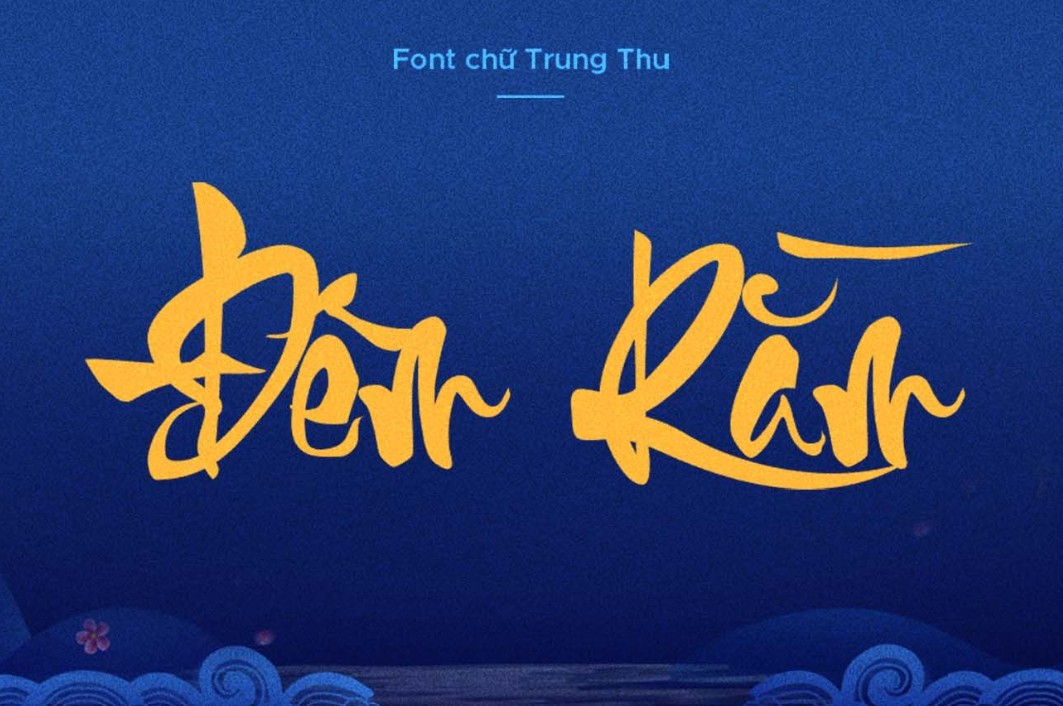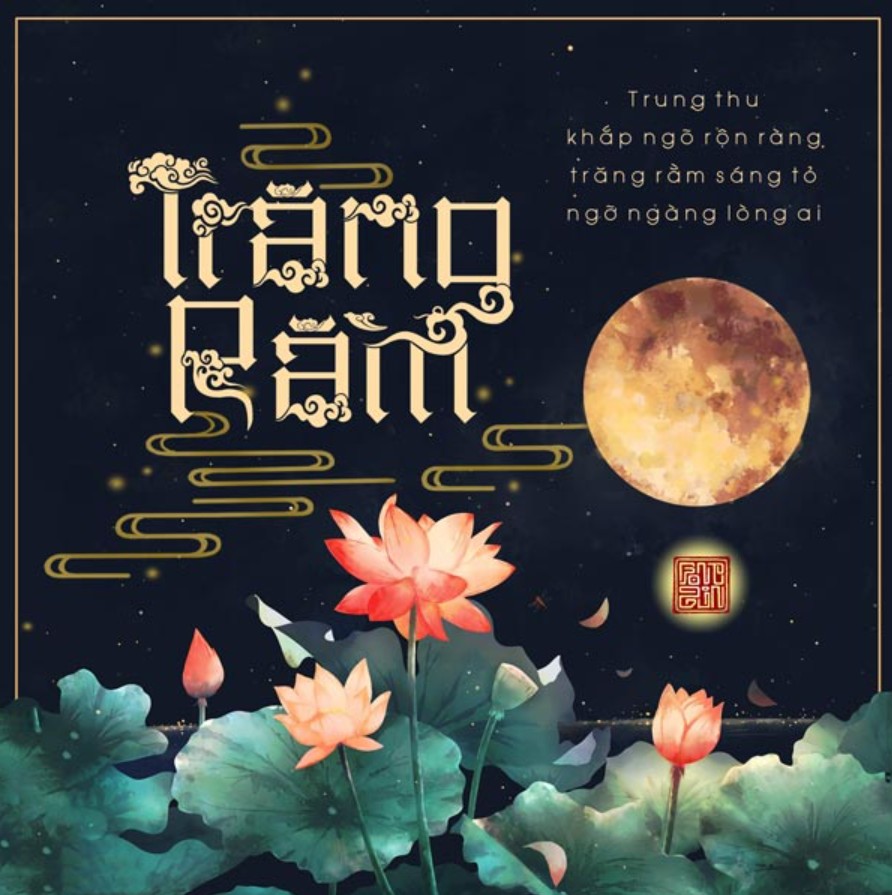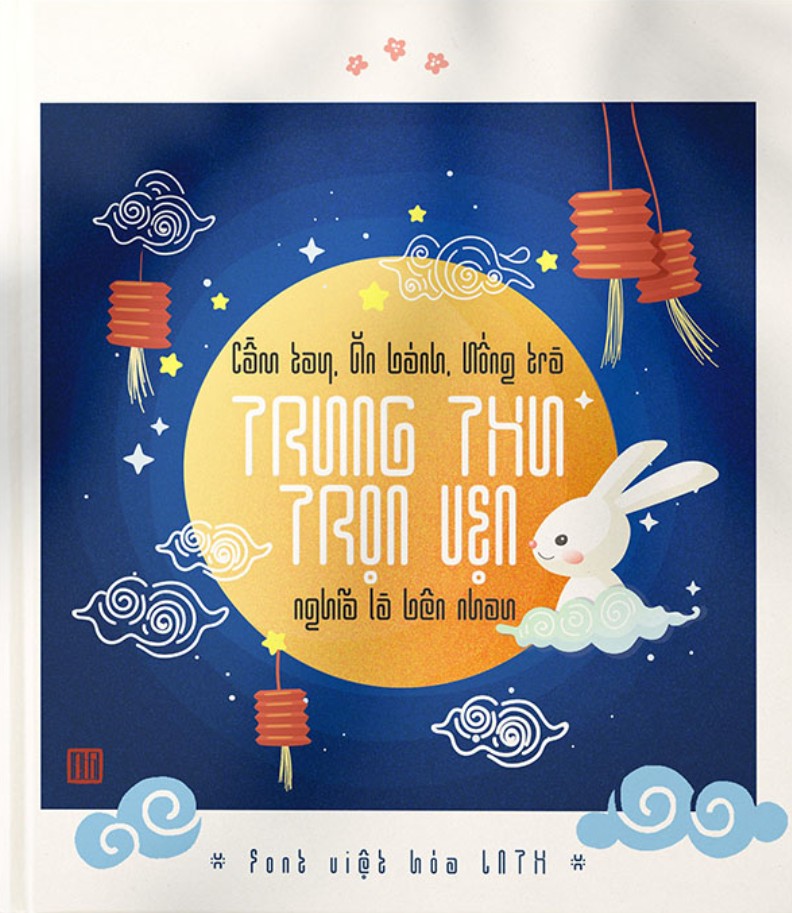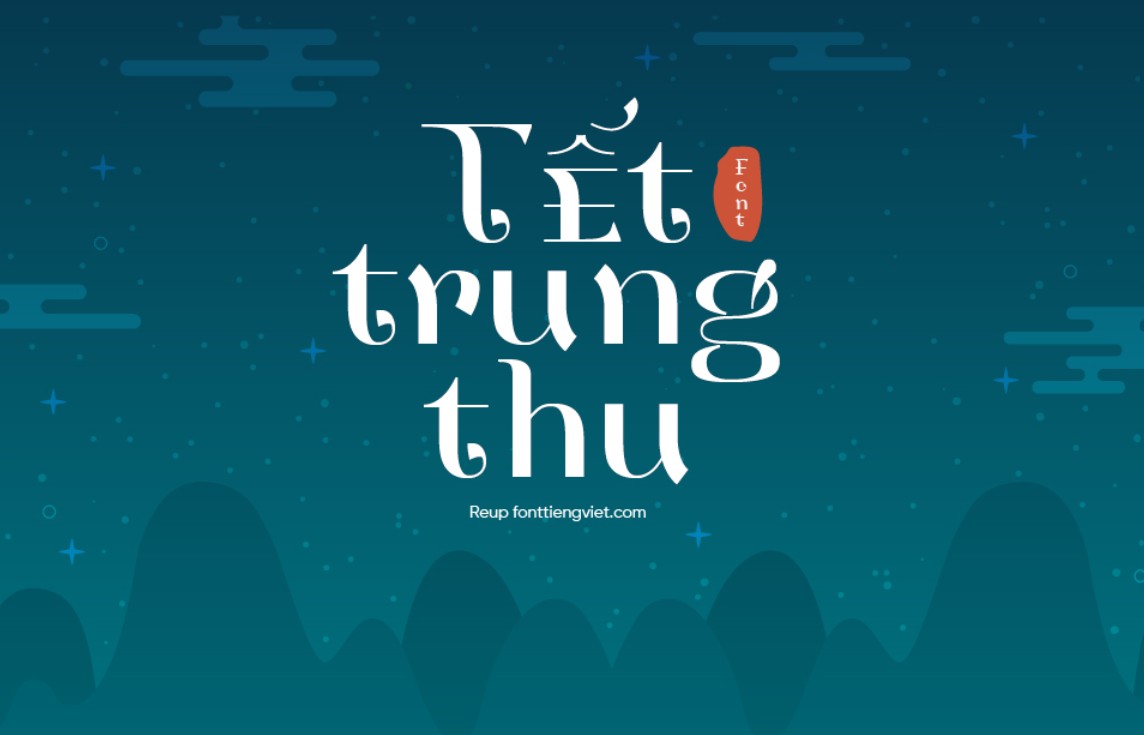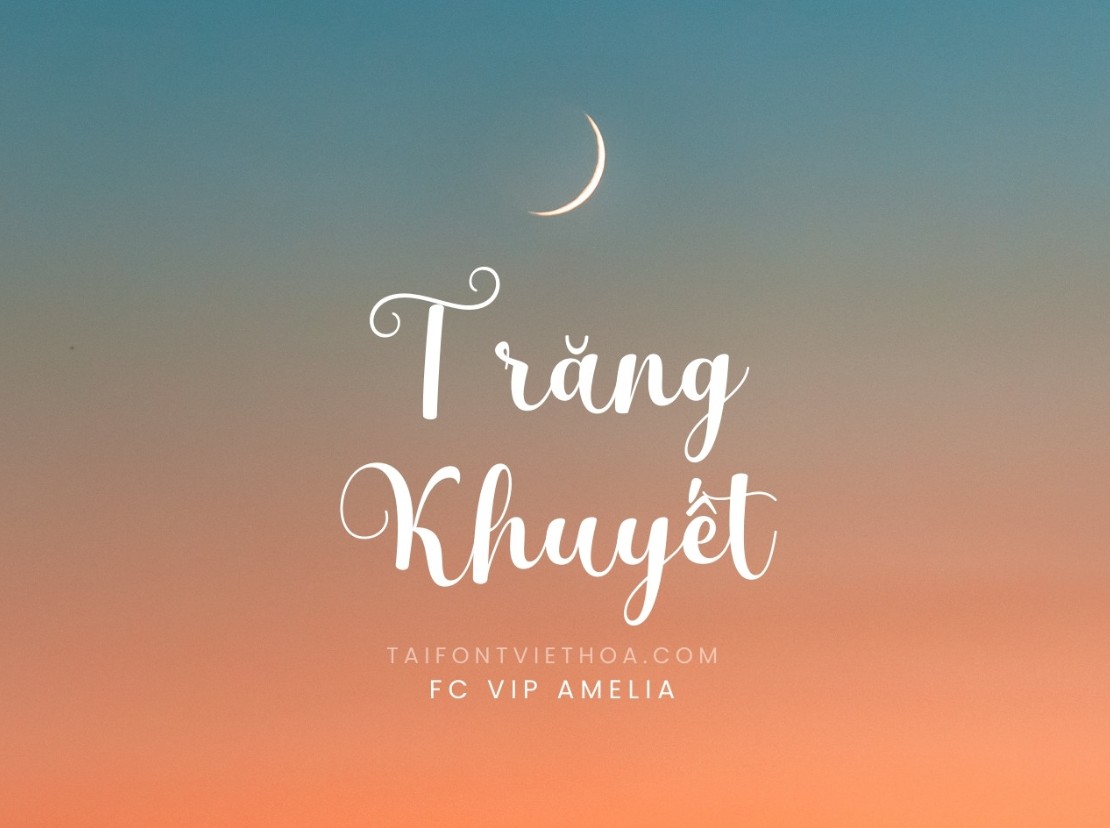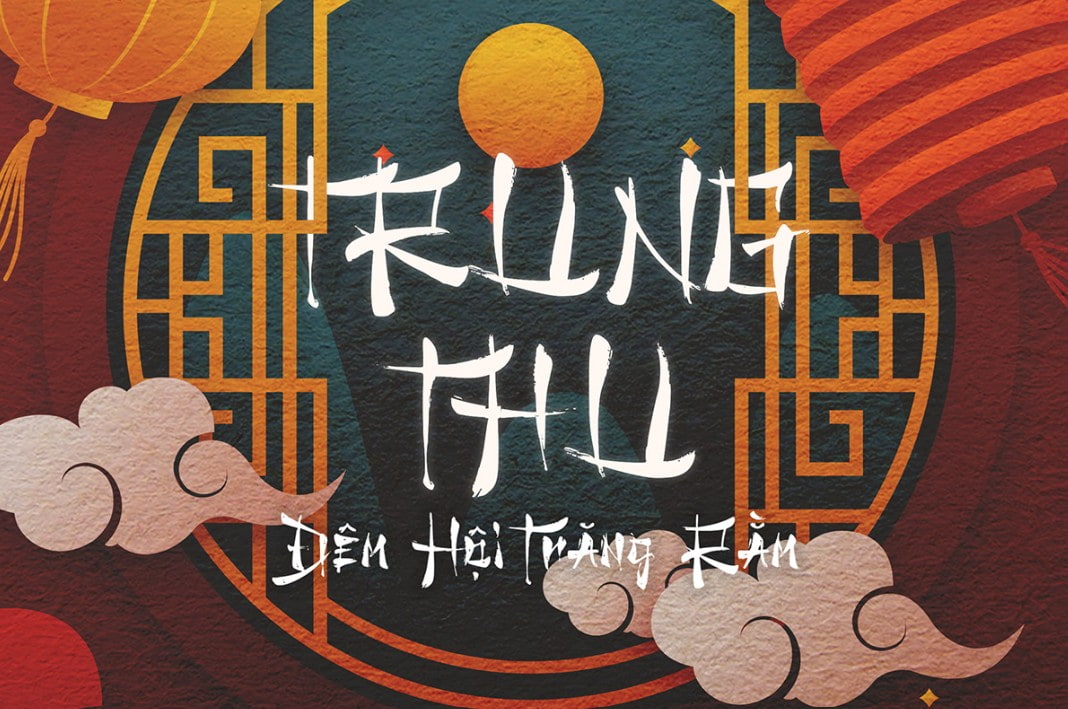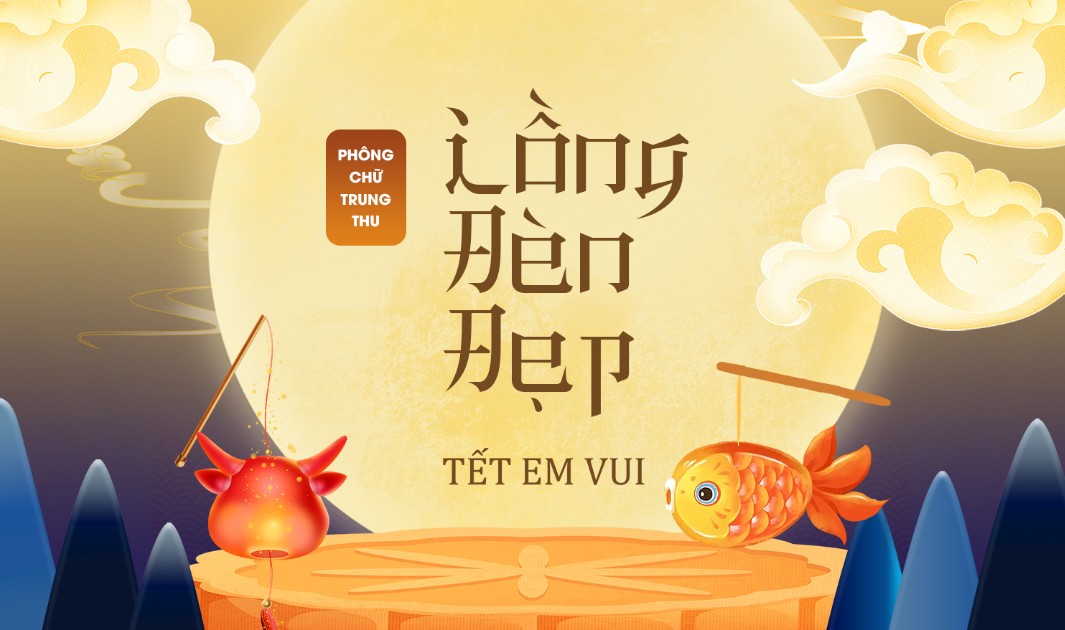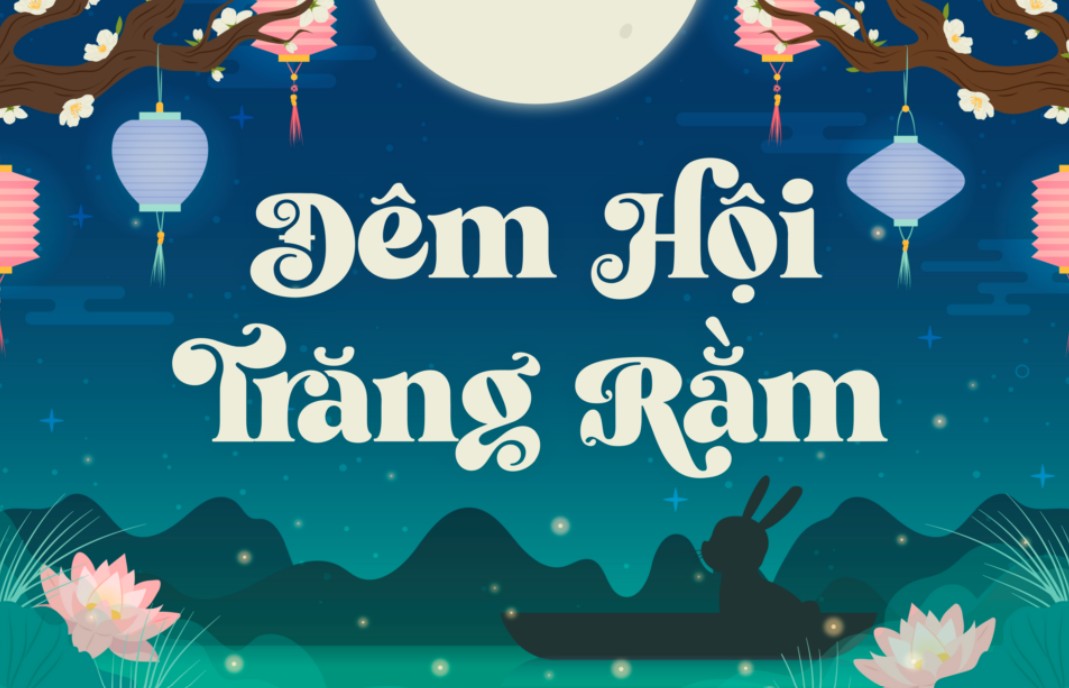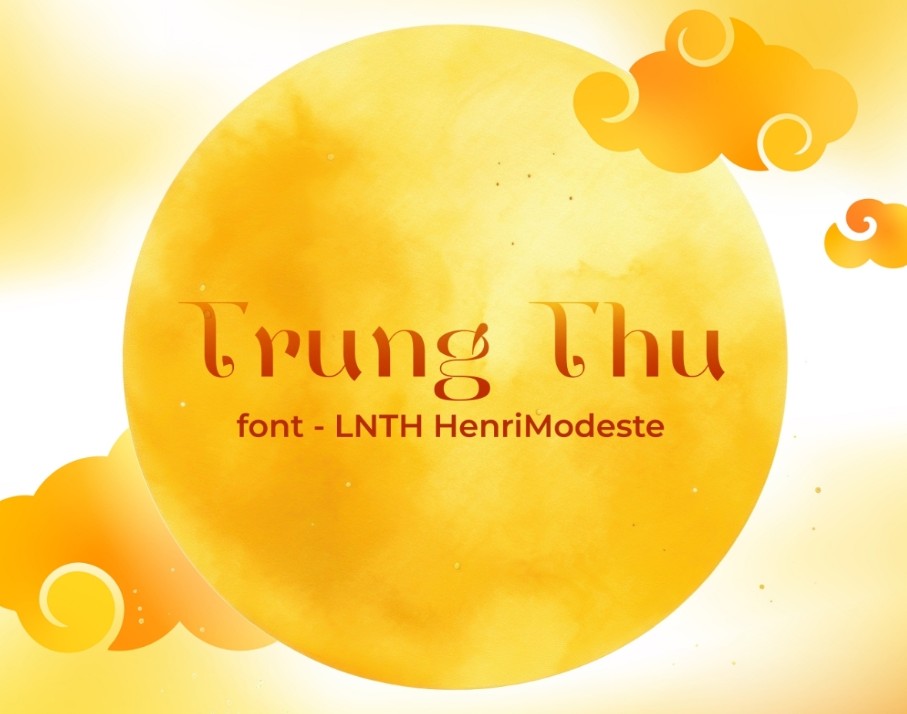
Các Nhóm Font Chữ Trung Thu Đẹp, Ấn Tượng Và Được Ưa Chuộng Nhất Hiện Nay
Font chữ Trung Thu là yếu tố quan trọng giúp truyền tải không khí đoàn viên, nét đẹp văn hóa truyền thống và phong cách riêng của từng thiết kế. Tùy theo mục đích sử dụng, bạn có thể lựa chọn nhóm font thư pháp cổ trang sang trọng, font viết tay hiện đại hoặc các kiểu chữ trang trí độc đáo.
Trong thiết kế ấn phẩm Trung Thu, font chữ đóng vai trò quan trọng không kém so với màu sắc, hình ảnh hay bố cục tổng thể. Một kiểu chữ phù hợp có thể giúp truyền tải trọn vẹn không khí đoàn viên, nét đẹp văn hóa truyền thống và cảm xúc ấm áp của đêm rằm tháng Tám.
Khác với các thiết kế thông thường, font chữ Trung Thu thường yêu cầu sự kết hợp giữa yếu tố hoài niệm và tính thẩm mỹ hiện đại. Những kiểu chữ mang phong cách thư pháp, cổ trang thường gợi cảm giác trang trọng, gần gũi với văn hóa Á Đông. Trong khi đó, các font viết tay hoặc hiện đại lại phù hợp với những thiết kế trẻ trung như thiệp chúc, bao bì sản phẩm, bài đăng mạng xã hội.
Năm nay, xu hướng lựa chọn font chữ Trung Thu tập trung vào sự mềm mại, giàu cảm xúc và khả năng kết hợp linh hoạt với các yếu tố trang trí như đèn lồng, trăng tròn, hoa văn dân gian, họa tiết cung trăng hoặc hình ảnh chú Cuội, chị Hằng.
Việc lựa chọn đúng nhóm font không chỉ giúp thiết kế đẹp hơn mà còn tạo ra sự nhất quán về phong cách, giúp người xem dễ dàng cảm nhận được tinh thần của mùa lễ hội. Dưới đây là những nhóm font chữ Trung Thu phổ biến được sử dụng nhiều trong thiết kế hiện nay.
1. Font thư pháp và cổ trang
Nhóm font thư pháp và cổ trang là lựa chọn quen thuộc trong các thiết kế Trung Thu mang phong cách truyền thống. Những kiểu chữ này thường có đường nét mềm mại, độ tương phản giữa nét thanh và nét đậm rõ ràng, tạo cảm giác sang trọng, sâu lắng và gợi nhớ đến nét đẹp văn hóa xưa.
Đây là nhóm font thường được sử dụng cho các vị trí quan trọng như tiêu đề chính, banner sự kiện, poster Trung Thu, logo chương trình hoặc các ấn phẩm quảng bá lễ hội. Do đặc điểm có nhiều đường nét bay bổng, nhóm font này giúp thiết kế trở nên nổi bật và tạo điểm nhấn thị giác ngay từ lần đầu nhìn thấy.
Một ưu điểm lớn của font thư pháp là khả năng kết hợp tốt với các yếu tố trang trí truyền thống. Khi đặt cạnh hình ảnh mặt trăng, đèn lồng, hoa sen, họa tiết mây, sóng nước hoặc màu sắc đỏ, vàng, cam, kiểu chữ này tạo nên tổng thể đậm chất Á Đông.
Tuy nhiên, khi sử dụng nhóm font này cần chú ý đến khả năng đọc. Những kiểu chữ quá cầu kỳ nếu dùng với nội dung dài có thể gây khó theo dõi. Vì vậy, chúng thường phù hợp nhất với những câu chữ ngắn như tên chương trình, lời chúc, slogan hoặc tiêu đề nổi bật.
1.1. LNTH Henri Modeste
LNTH Henri Modeste là một trong những font chữ được yêu thích trong các thiết kế mang hơi hướng cổ điển. Font có đặc điểm nổi bật là sự kết hợp giữa nét thanh và nét đậm, tạo cảm giác mềm mại nhưng vẫn giữ được sự trang trọng.
Kiểu chữ này mang lại cảm giác hoài cổ, phù hợp với những thiết kế muốn tái hiện không khí Trung Thu truyền thống như đêm rước đèn, không gian phố cổ hoặc các chương trình văn hóa dân gian.
Khi sử dụng LNTH Henri Modeste, người thiết kế thường ưu tiên đặt trên nền màu ấm như vàng ánh trăng, đỏ đô hoặc xanh đậm để làm nổi bật vẻ đẹp cổ điển của font chữ.
1.2. UTM Yen Tu/Shitian
UTM Yen Tu và Shitian là nhóm font có phong cách gần với chữ viết thư pháp truyền thống. Các đường nét được thiết kế uyển chuyển, tạo cảm giác tự nhiên như nét bút viết tay.
Nhóm font này đặc biệt phù hợp với các thiết kế muốn truyền tải sự bình yên, nhẹ nhàng và đậm chất lễ hội Trung Thu. Những câu chúc như “Trung Thu Đoàn Viên”, “Đêm Hội Trăng Rằm” hoặc tên các chương trình thiếu nhi thường sử dụng kiểu chữ này để tạo cảm xúc gần gũi.
Khi kết hợp với hình ảnh lồng đèn, trăng sáng hoặc các họa tiết dân gian, UTM Yen Tu và Shitian giúp thiết kế có chiều sâu hơn, vừa truyền thống vừa giàu tính nghệ thuật.
1.3. LNTH Hieroglyphic
LNTH Hieroglyphic là font chữ mang phong cách độc đáo hơn khi kết hợp giữa chữ viết cổ điển và các chi tiết hoa văn trang trí.
Điểm đặc biệt của font này nằm ở cảm giác bí ẩn, nghệ thuật và có phần khác biệt so với các kiểu chữ thư pháp thông thường. Đây là lựa chọn phù hợp cho các thiết kế cần tạo dấu ấn riêng như logo Trung Thu, tiêu đề bộ sưu tập, bao bì sản phẩm cao cấp hoặc các chương trình mang phong cách sáng tạo.
Tuy nhiên, vì font có nhiều yếu tố trang trí nên cần sử dụng có chọn lọc. Việc kết hợp quá nhiều họa tiết xung quanh có thể khiến tổng thể thiết kế trở nên rối mắt.
2. Font viết tay và hiện đại
Bên cạnh phong cách truyền thống, nhóm font viết tay và hiện đại ngày càng được sử dụng phổ biến trong các thiết kế Trung Thu trẻ trung.
Nhóm font này có ưu điểm là dễ tiếp cận, tạo cảm giác thân thiện và gần gũi hơn. Nếu font thư pháp thường mang vẻ trang trọng thì font viết tay lại tạo cảm giác ấm áp, tự nhiên như một lời nhắn gửi cá nhân.